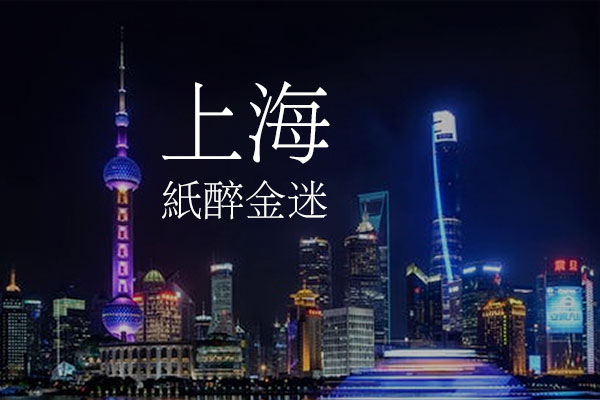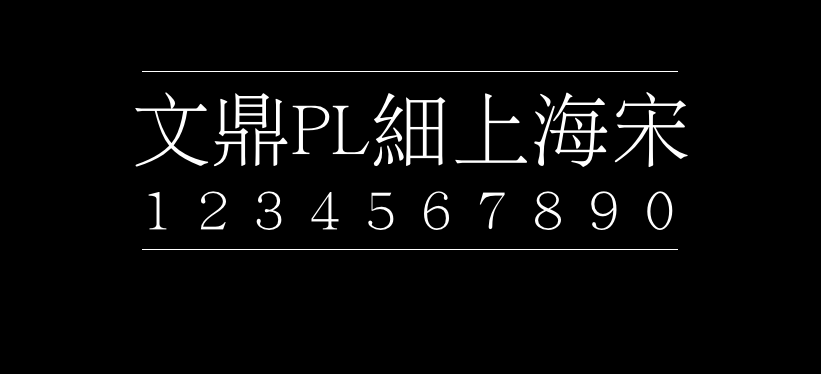
文鼎PL细上海宋
文鼎PL细上海宋(AR PL Mingti2L Big5 Regular)是Linux操作系统上最早的高质量开源中文字体,是文鼎科技于免费提供捐赠予自由软件社区的一套宋体字体。这套宋体字体字形比较纤细,比较适合偏优雅古风的设计风格。
字体名称中的“PL”并不是指漂亮,而是代表这款字体是公众授权Public License。文鼎科技共免费提供了4套公众授权的字体,这四款字体分别是:文鼎PL简中楷、文鼎PL中楷体(BIG5)、文鼎PL细上海宋、文鼎简报宋,需要的可以在本站搜索下“文鼎”即可获得。